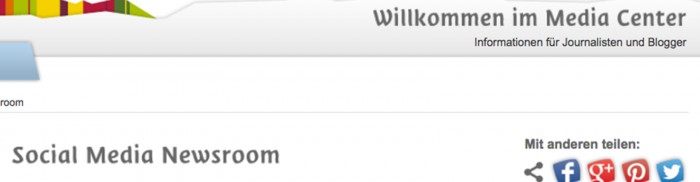
CI-Schrift auf Südtirol-Website
Ich finde die Schrift im Beispiel (leider habe ich kein besser aufgelöstes Beispiel) recht bemerkenswert und würde sie gerne mal testen. Wer kennt den Namen des verwendeten Fonts ("Willkommen im Media Center" "Social Media Newsroom")?
Das ist eine eigens entwickelte Hausschrift, die darfst du nur dann einsetzen, wenn du im Auftrag der Agentur Südtirol Marketing (SMG) tätig bist, dann bekommst du sie auch dort. Sonst nicht.